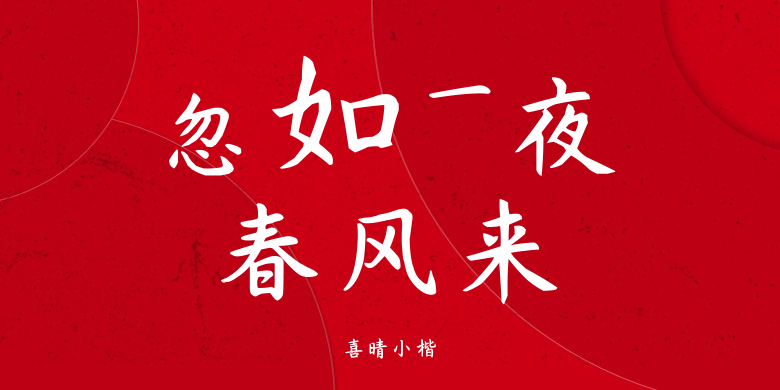
喜晴小楷
喜晴小楷,这款字体结构工整、笔画清晰,兼顾美观与易读性,适用于标题、正文、海报、包装、LOGO 等多种场景。字形优雅稳定,风格百搭耐看,适配日常排版与创意设计,让文字呈现更舒适、更具质感。喜晴小楷一笔一画,皆是细节,以均衡的比例、流畅的线条打造舒适视觉体验,字形端正大气,风格简约现代。无论是商业设计、品牌宣传还是日常排版,都能轻松驾驭,让文字更有格调与力量。喜晴小楷字体下载。